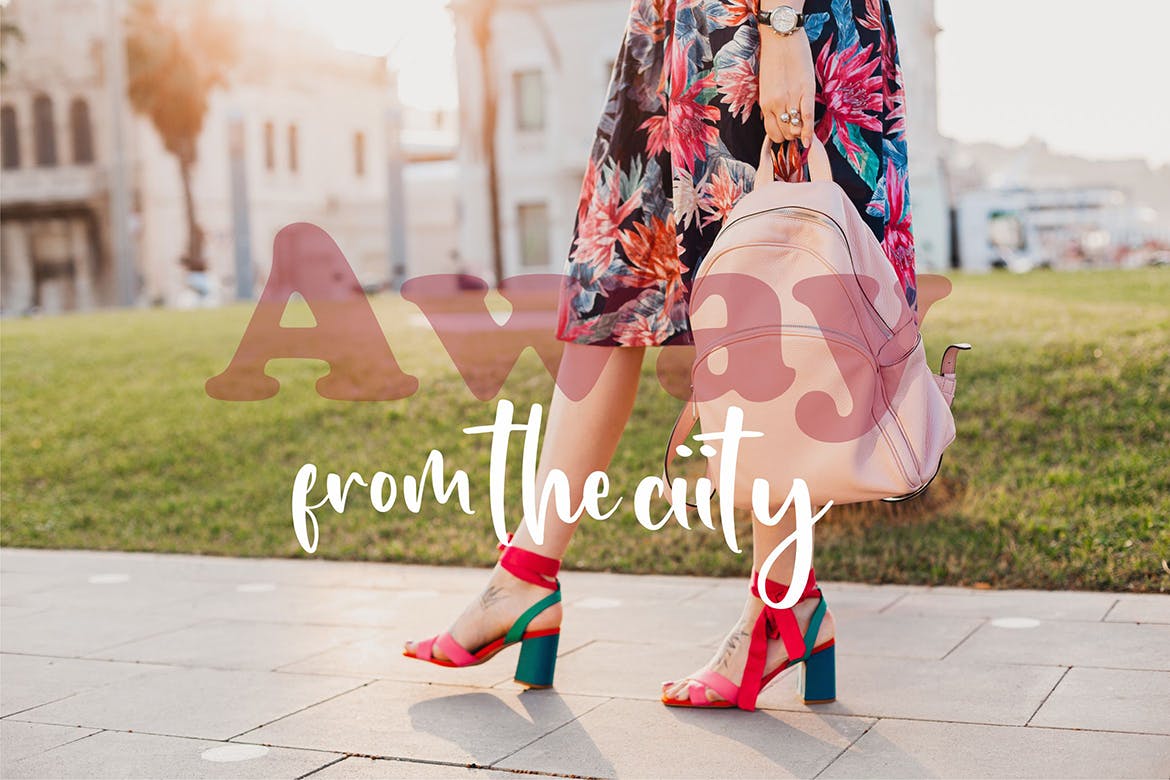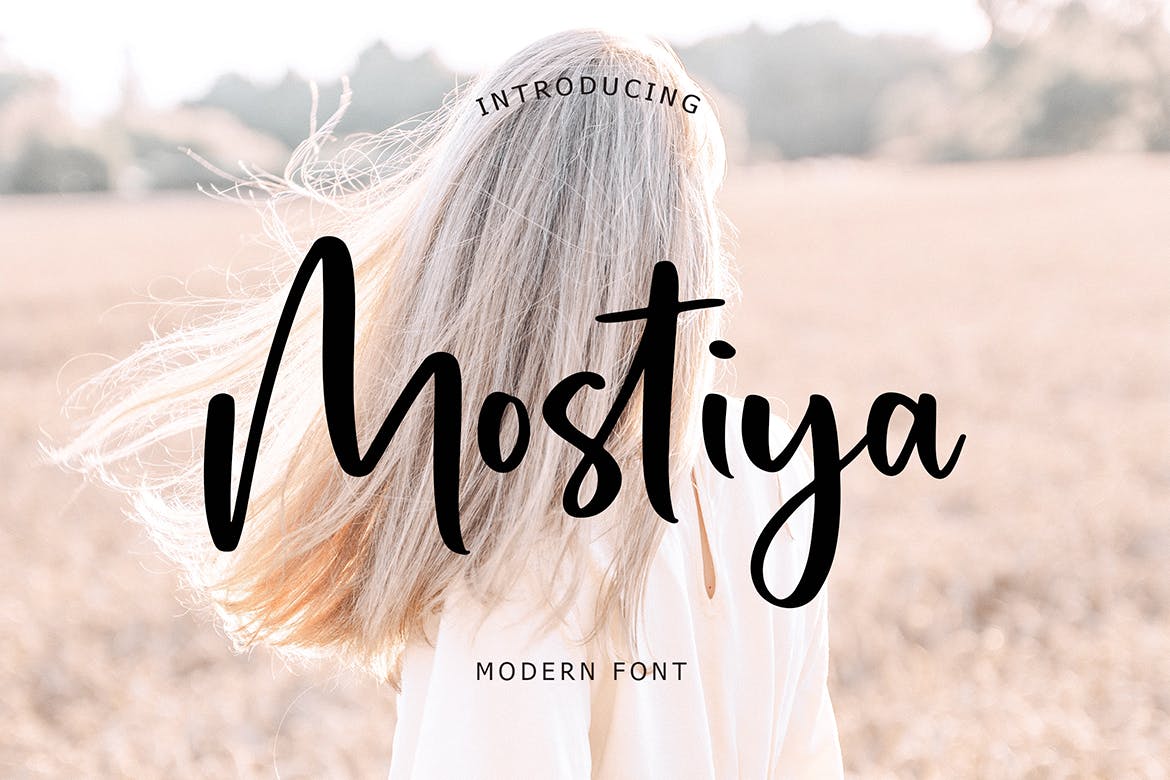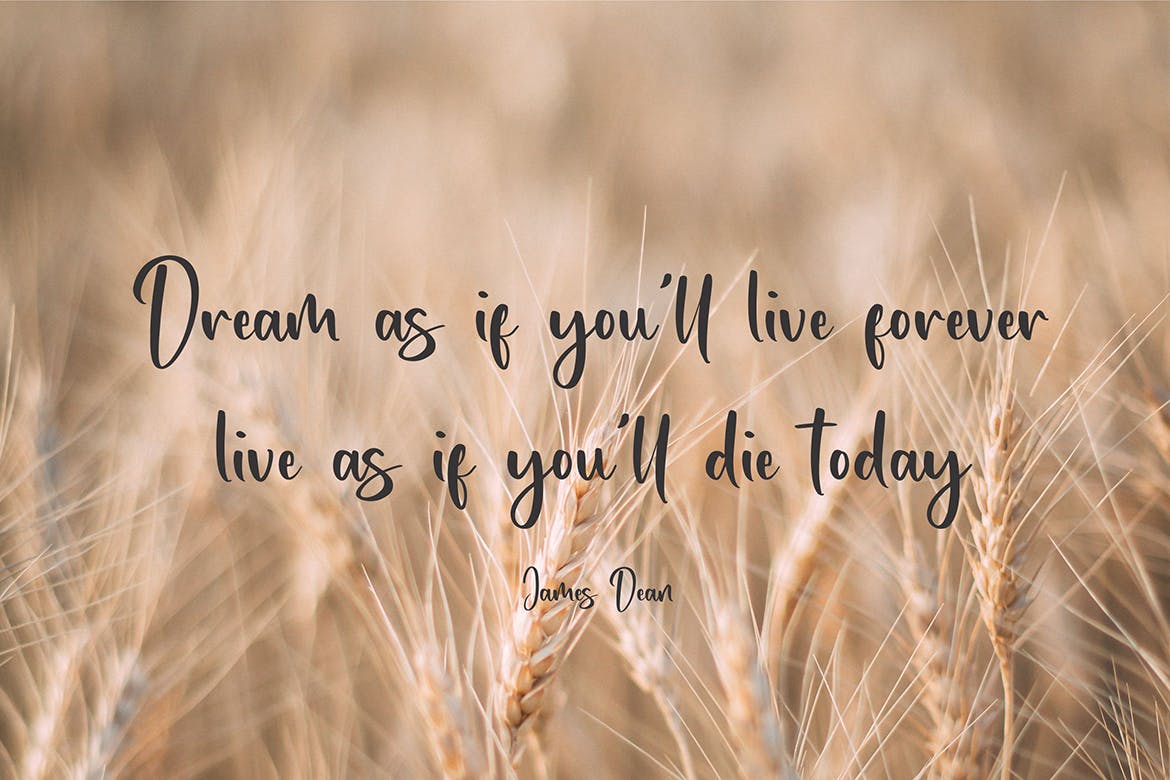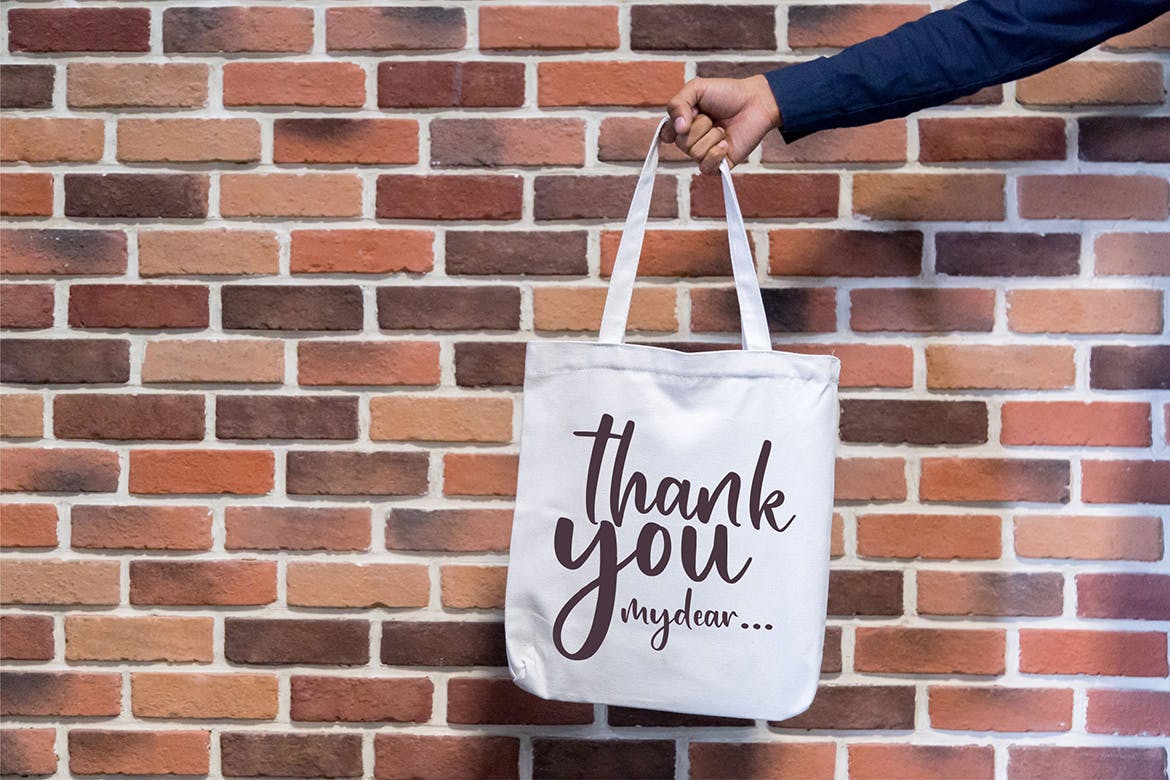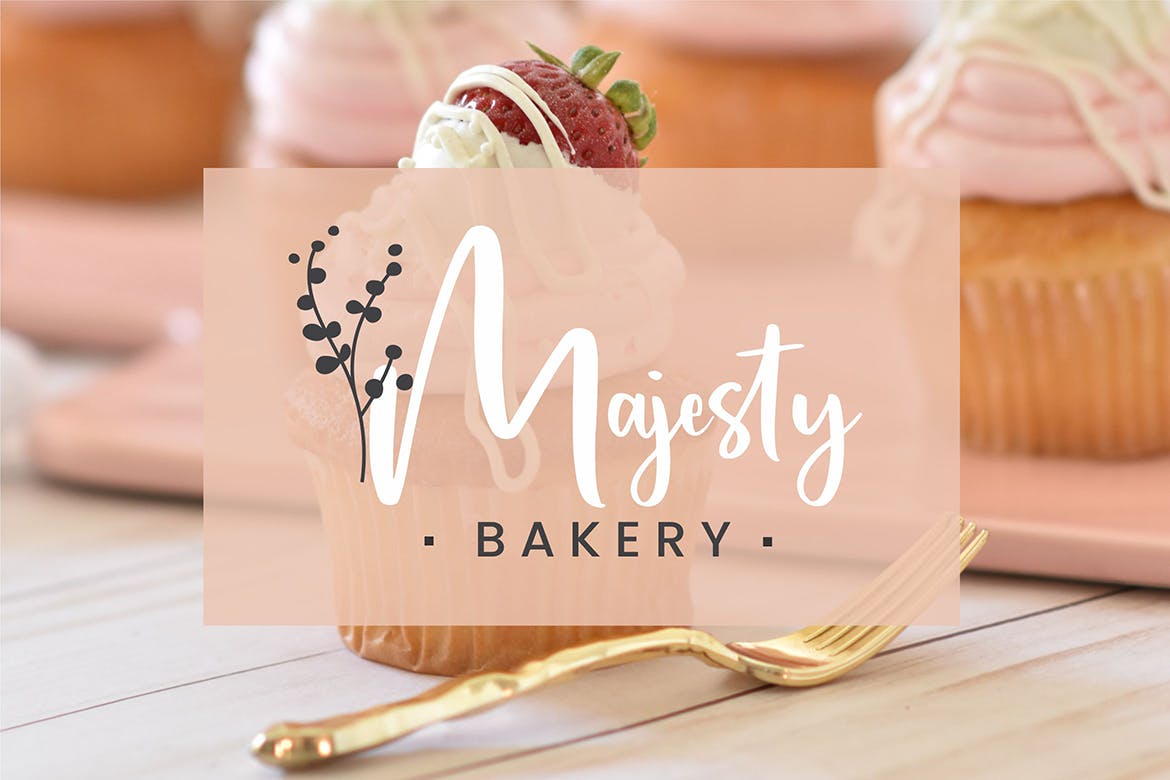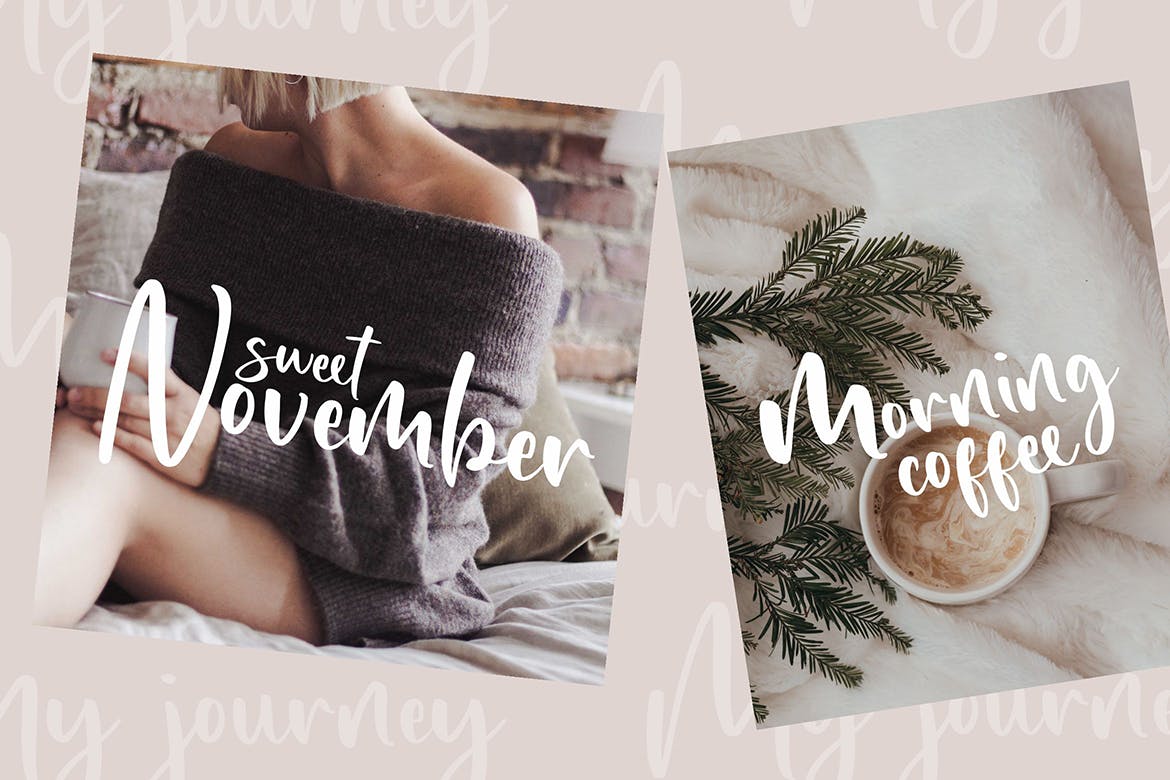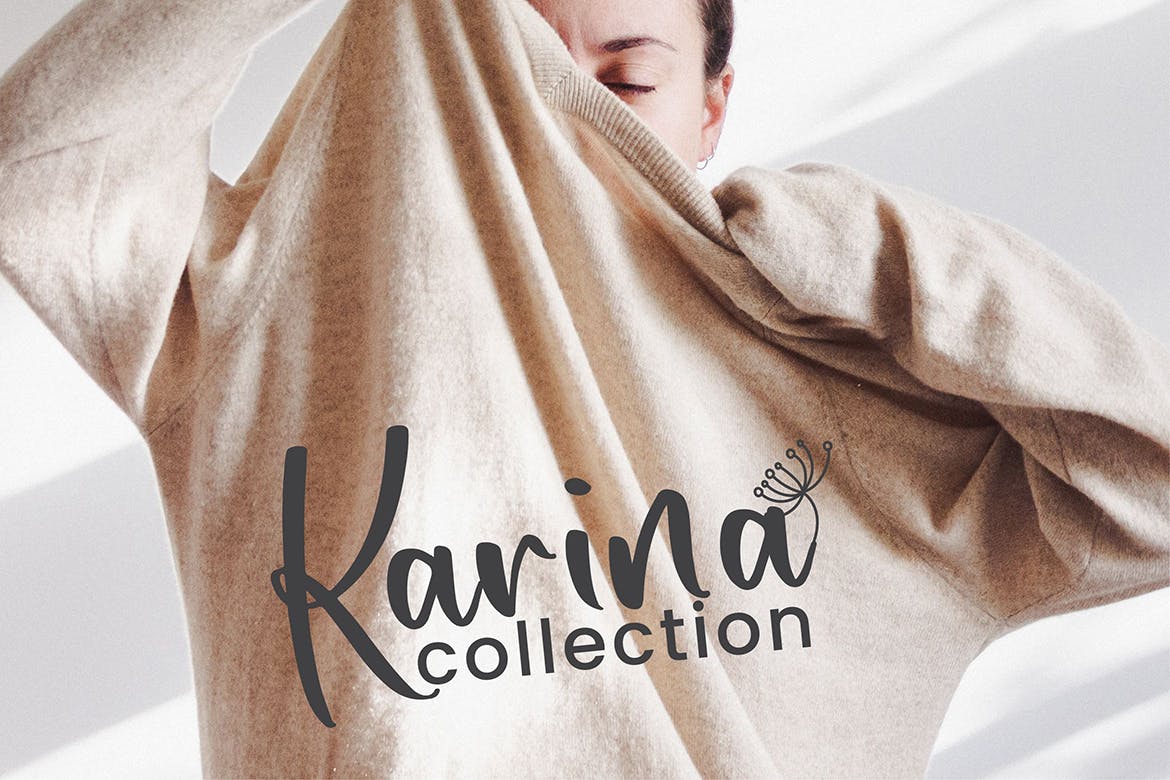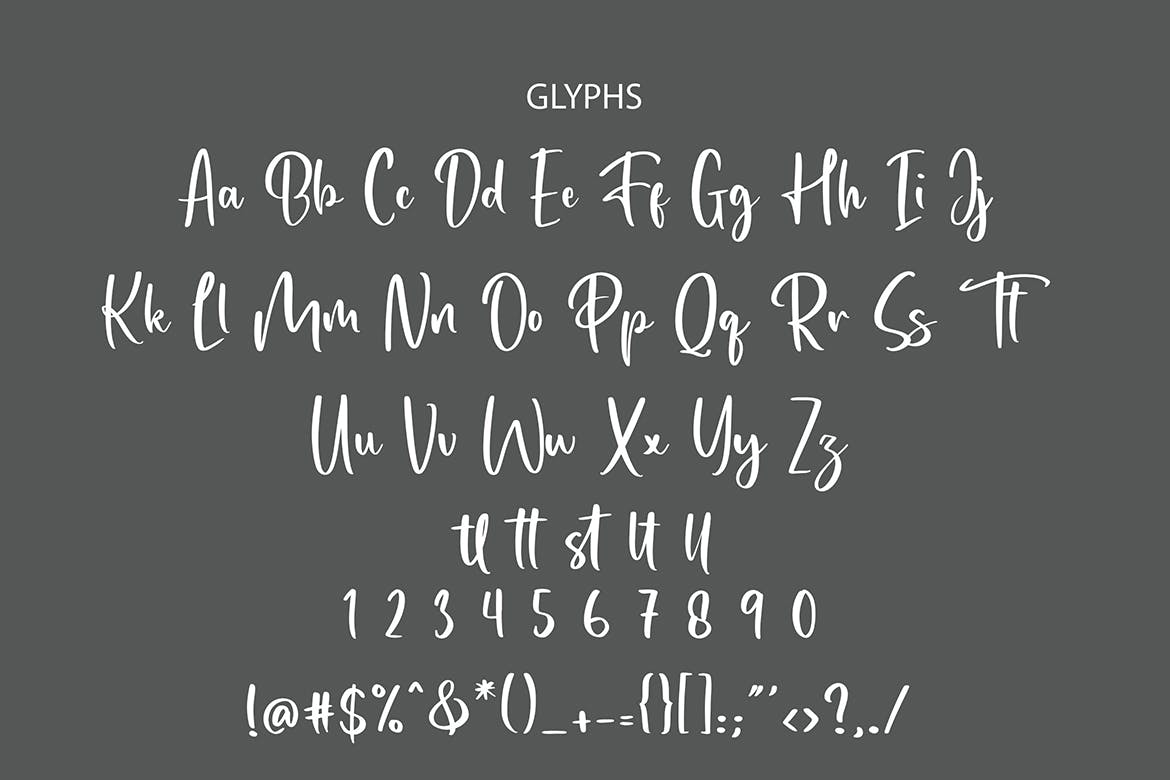
Mostiya یک فونت مدرن و زیباست که به هر پروژه طراحی حس ظرافت و زیبایی میبخشد.
فونت Mostiya برای پروژههای برندینگ، لوگو، طراحیهای عروسی، پستهای شبکههای اجتماعی، تبلیغات، بستهبندی محصولات، طراحی محصولات، برچسب، عکاسی، واترمارک، دعوتنامه، لوازمالتحریر و هر نوع پروژه دیگری مناسب است.